Font chữ chấm bi là nhóm phông chữ đặc thù được cấu thành từ tập hợp các điểm tròn riêng lẻ xếp liền nhau theo một trật tự ma trận hình học chặt chẽ. Lấy cảm hứng từ các bảng đèn LED điện tử, biển hiệu rạp hát cổ điển gắn bóng tròn và kỹ thuật đục lỗ kim loại tấm, kiểu chữ này giúp các kiến trúc sư, nhà thiết kế mang lại sự phá cách cho các bản vẽ phối cảnh mặt tiền quán cà phê container, khu vui chơi giáo dục hay hệ thống biển báo tương tác.
Cấu trúc ma trận hạt tròn và hiệu ứng thị giác đục lỗ của font chữ chấm bi
Điểm cuốn hút của font chữ chấm bi nằm ở sự kết hợp giữa tính kỷ luật số học và hiệu ứng thị giác bán trong suốt. Thay vì các mảng màu đặc kín, các con chữ được hình thành từ khoảng trống và các điểm tròn lặp lại, tạo nên cảm giác nhẹ nhõm, hiện đại và rất giàu tính công nghệ.
Sự ổn định về mặt thị giác của dòng font này giúp thông điệp truyền thông trở nên nổi bật vào ban đêm khi kết hợp cùng các giải pháp ánh sáng. Khi xuất hiện trên các bề mặt vật liệu kiến trúc như tấm tôn đục lỗ, alu đột lỗ CNC gắn đèn LED hay vách kính dán decal chấm bi, kiểu chữ này tạo nên hiệu ứng thị giác chuyển động vô cùng sinh động.
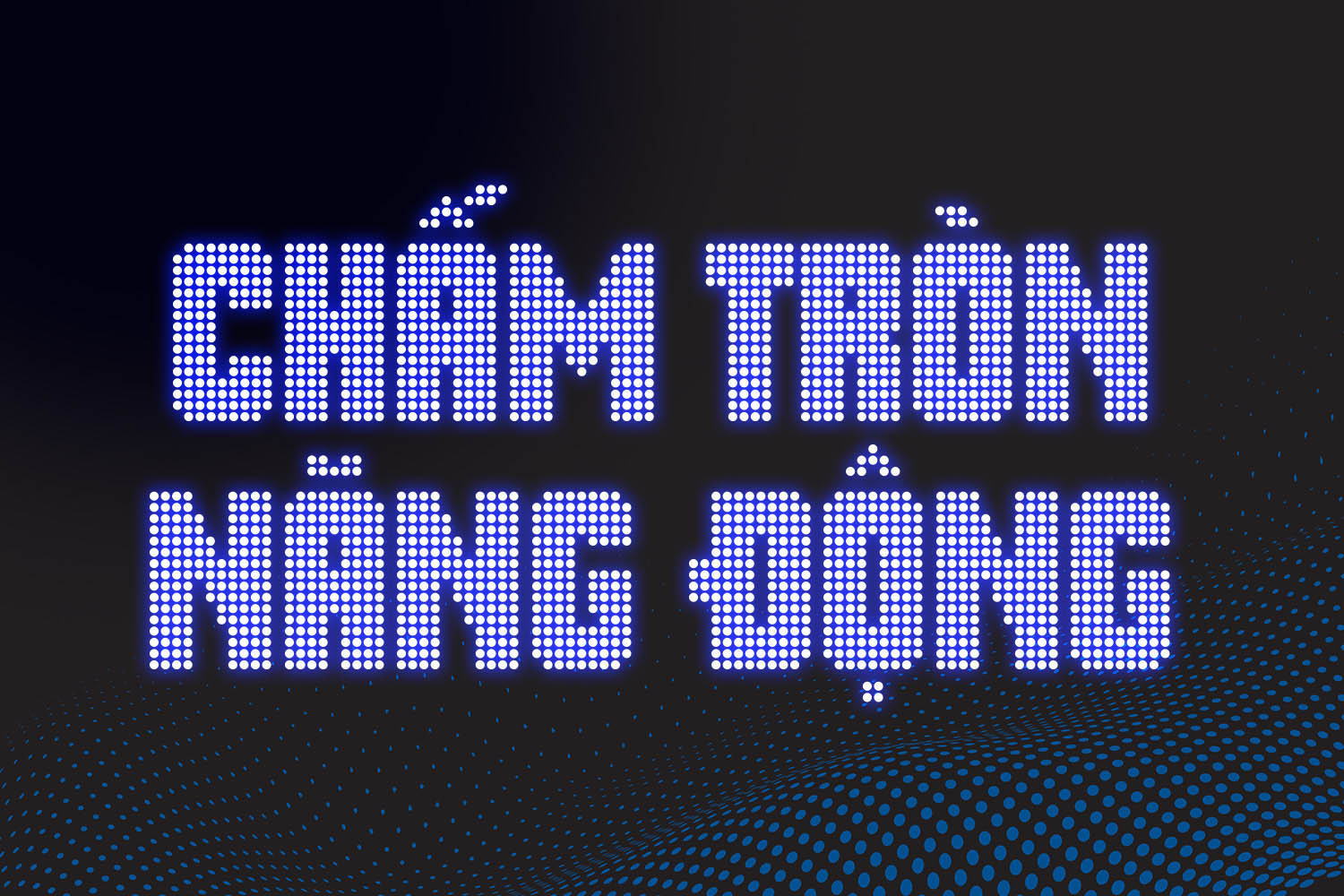
Tư vấn từ chuyên viên: Font chữ chấm bi sở hữu đặc thù thị giác dạng hạt rời rạc. Để bản thiết kế đạt hiệu quả thẩm mỹ tốt, bạn nên sử dụng phông chữ này cho các tiêu đề chính, tên thương hiệu hoặc con số kỹ thuật ở kích thước lớn. Phần nội dung mô tả chi tiết nên đi kèm một phông chữ không chân nét liền để người xem tiếp nhận thông tin dễ dàng.
03 Ứng dụng phông chữ chấm bi vào công trình thực tế
Nhờ vẻ ngoài hiện đại và tính kết nối cao với kỹ thuật gia công cơ khí, bộ phông chữ này mang lại giá trị thực tế lớn trong khâu hoàn thiện các dự án xây dựng:
- Biển hiệu kim loại tấm đục lỗ cho Quán Cafe Container: Những ký tự hạt tròn của phông chữ này rất ăn ý khi lập trình đột lỗ CNC trực tiếp lên vách tôn sóng container hoặc tấm sắt đen, phía sau gắn đèn LED chiếu sáng xuyên thấu vào ban đêm, tạo hiệu ứng thị giác rực rỡ.
- Hệ thống biển chỉ dẫn Khu vui chơi và Không gian trải nghiệm: Phông chữ này khi in trên kính cường lực hoặc bảng mica trong suốt sẽ giúp các khu vực chức năng trong nhà lắp ghép toát lên chất công nghệ số, thu hút sự chú ý của trẻ em và giới trẻ.
- Bìa hồ sơ giải pháp chiếu sáng kiến trúc (Lighting Concept): Sử dụng tải font chữ chấm bi cho tên dự án giúp tập hồ sơ trông như một ấn phẩm công nghệ hiện đại, thể hiện năng lực sáng tạo của đơn vị thiết kế đối với chủ đầu tư.
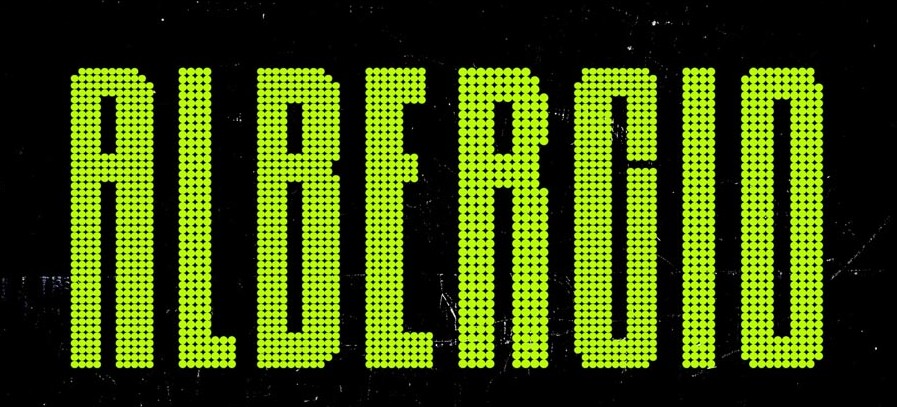
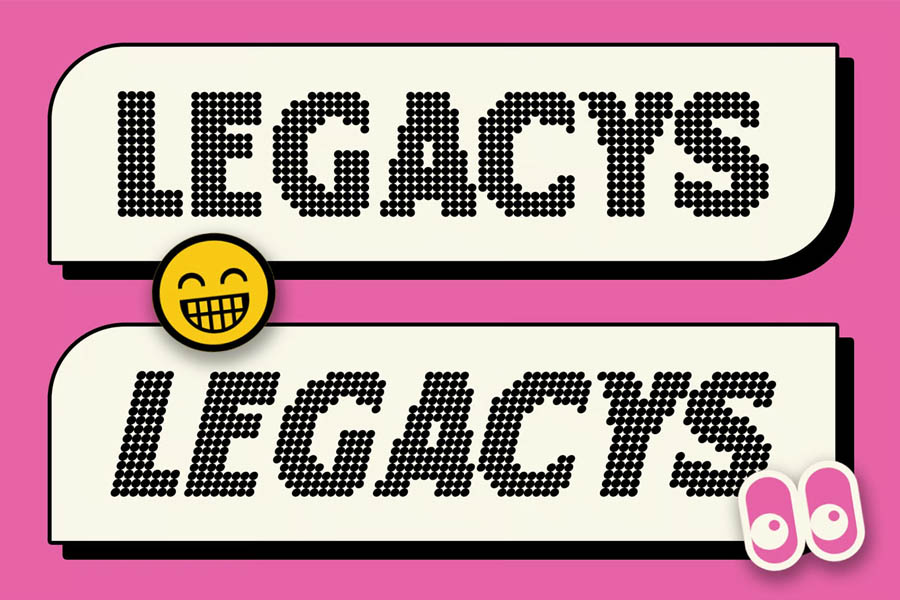
03 Lưu ý bố cục download font chữ chấm bi đạt độ rõ nét trên vật liệu
Để khai thác hiệu quả vẻ đẹp của dòng font ma trận điểm này mà không gây cảm giác khó nhìn cho bản vẽ, người thiết kế nên lưu tâm một số kinh nghiệm sau:
- Kiểm soát kích thước đường kính hạt chấm: Khi xuất file gia công cơ khí (cắt laser, đột CNC), bạn cần tính toán đường kính các hạt tròn và khoảng cách giữa các lỗ đục sao cho phù hợp với độ dày vật liệu, tránh hiện tượng rách mép kim loại sau khi thi công.
- Tránh sử dụng cho văn bản dài: Cấu trúc hạt rời rạc của phông chữ chấm bi không phù hợp cho các đoạn văn bản giải thích kỹ thuật dài. Hãy giới hạn trong các cụm từ ngắn từ 2 đến 4 từ hoặc các con số để tạo điểm nhấn thị giác tập trung.
- Lựa chọn gam màu tương phản cao: Phông chữ phát huy hiệu quả thị giác cao khi phối cùng các tông màu mang tính phát sáng như vàng chanh, xanh neon, trắng tinh khôi trên nền tối mờ, mô phỏng sinh động các bảng điện tử ban đêm.
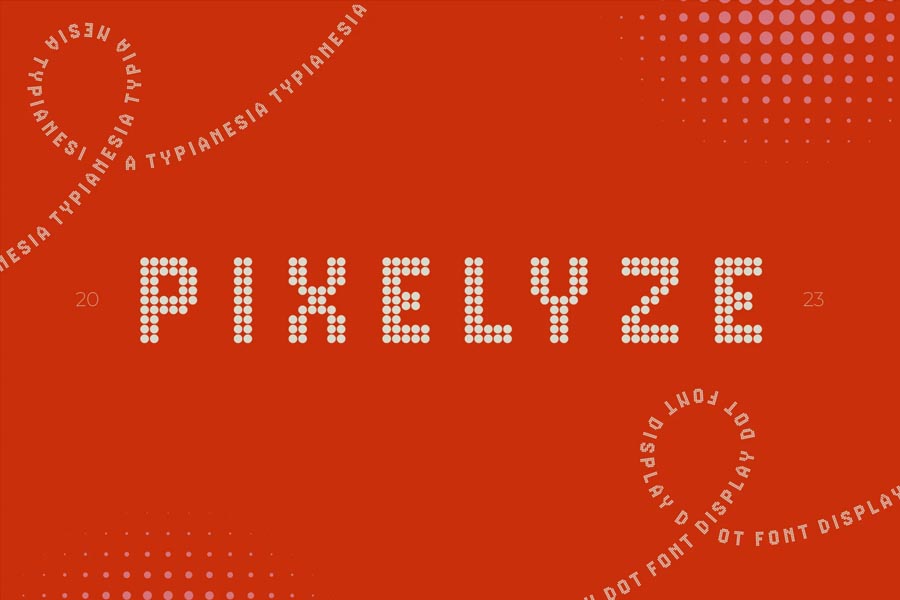
FAQs – Thắc mắc thường gặp khi sử dụng phông chữ chấm bi
2. Phông chữ này có hỗ trợ đầy đủ các ký tự số không?
Có. Bộ phông chữ chấm bi đã được tích hợp đầy đủ hệ thống chữ số dạng ma trận điểm đồng điệu, rất thuận tiện cho việc trình bày số phòng, bảng đồng hồ thời gian hay số tầng công trình.